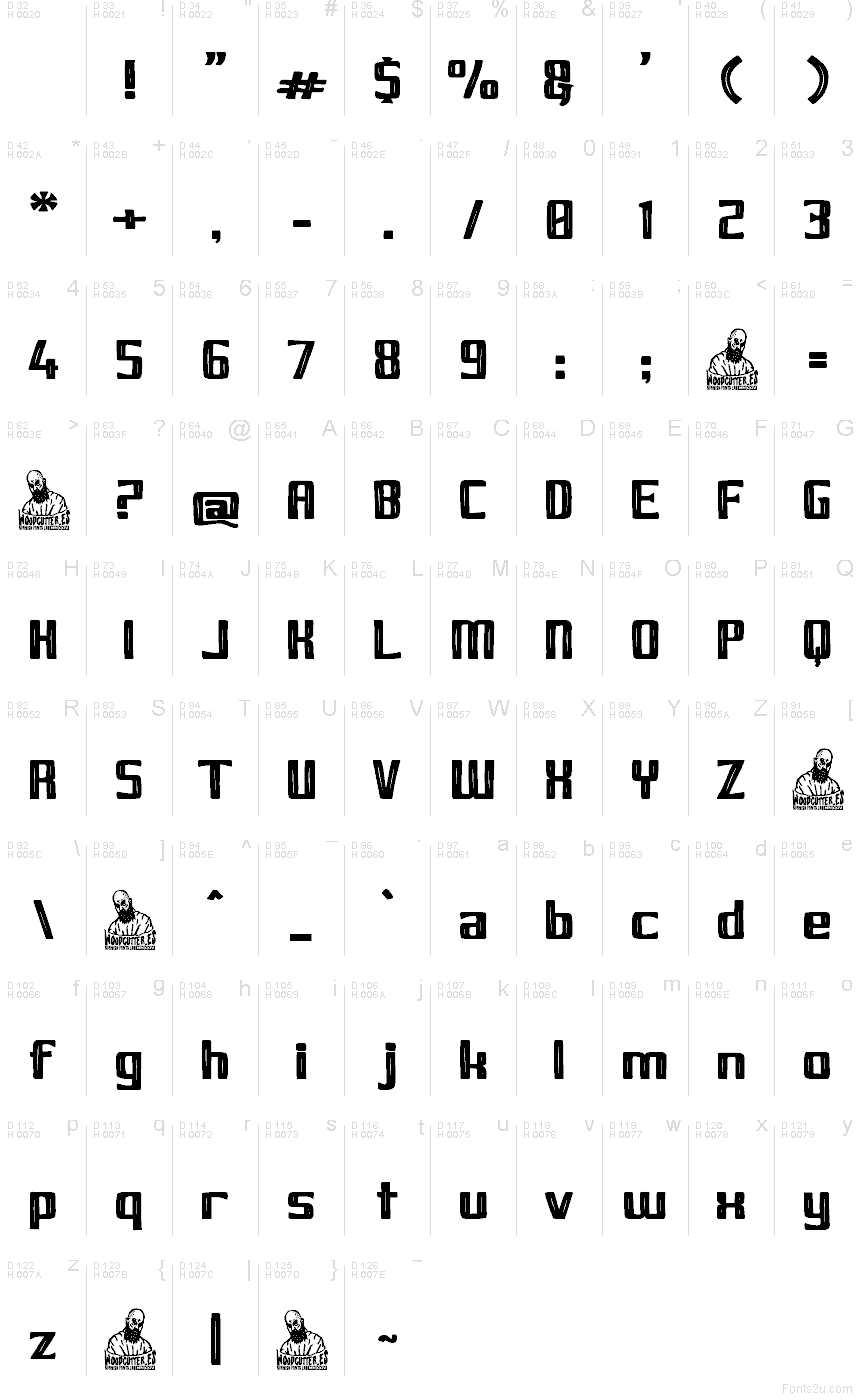
Podgląd czcionki Hotel Hanoi Royal
Hotel Hanoi Royal od Woodcutter Manero to bezpłatny, ręcznie malowany krój typu display, który oddaje klimat starych szyldów ulicznych i niezobowiązujących napisów sklepowych. Litery są wysokie, masywne i lekko nierówne, z zaokrąglonymi rogami oraz efektem suchego pędzla, co nadaje stylowi swobodny, a nie wygładzony charakter.
To naturalny wybór do tytułów na plakatach, identyfikacji wizualnej barów i kawiarni, opakowań w stylu podróżniczym, okładek zinów oraz ulotek wydarzeń, gdzie darmowy font powinien wyglądać ludzko i nieco improwizacyjnie. Sprawdza się również w krótkich nagłówkach i znakach graficznych (logotypach), ponieważ jego zwarte, pionowe kształty przypominają raczej szybko namalowany napis niż formalny krój dekoracyjny.